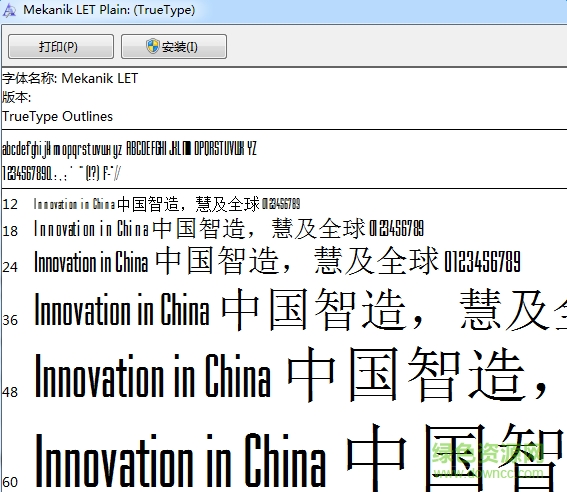
MEKANIKLETPLAIN英文字體
MEKANIKLETPLAIN字體是一款超好用的英文個性字體,該字體整體的排版效果非常好,讓用戶能夠收到一種不一樣的廣告設(shè)計效果,非常適合平面設(shè)計的用戶使用,歡迎來綠色資源網(wǎng)下載。
MEKANIKLETPLAIN字體
MEKANIKLETPLAIN字體是一款極具個性的字體,該字體十分飄逸,彰顯了自己的個性,有喜歡的朋友可以來綠色資源網(wǎng)下載使用!